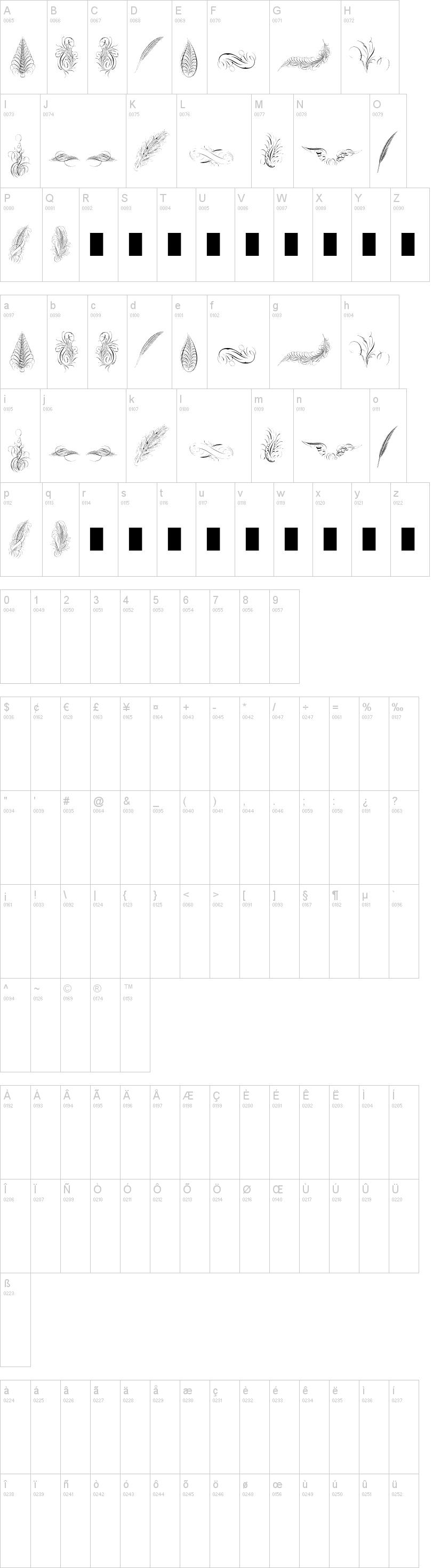
Penmanship Feathers
? Penmanship Feathers 是一款精美的手写字体,它受到了西方文化的影响,以及美国手写字体的灵感。它拥有细腻、流畅的笔画,可以带来温暖、友好的感觉,非常适合用于礼品卡、明信片、海报、婚礼邀请函等印刷品的设计。
Penmanship Feathers是一款非常不错的手写艺术字体,具有很好的视觉感,适合于文化类的宣传设计、商业类品牌的广告和产品包装设计以及个性化文字排版等较多场景。
Penmanship Feathers字符映射图